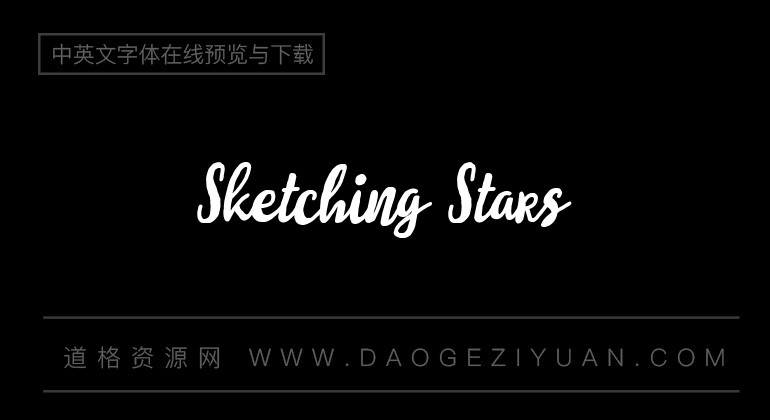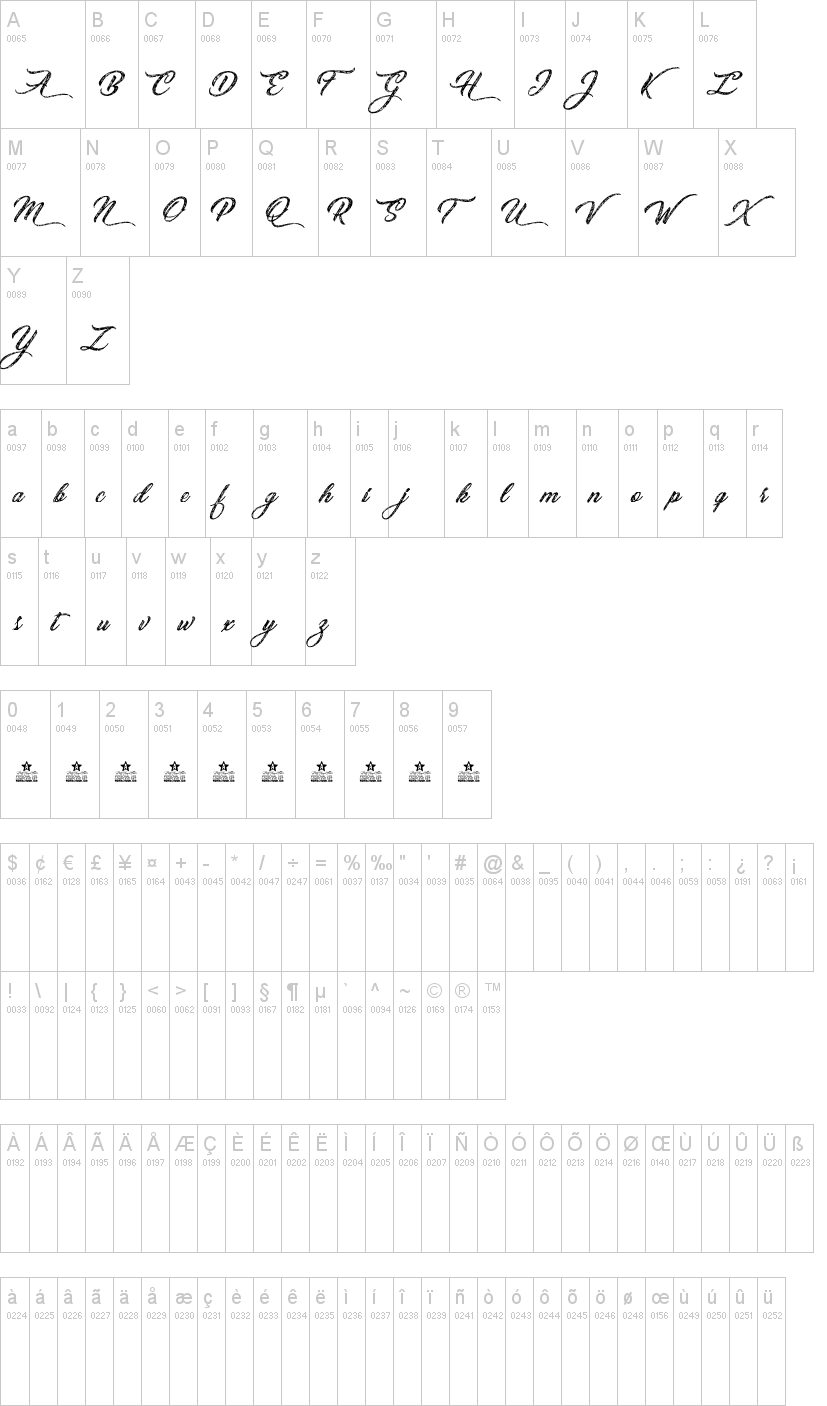
Sketching Stars
? Sketching Stars 字体是一款手绘风格的字体,它具有柔和的线条,可以更好地把握文本的精神内涵,更有助于传达出设计师的创意想法。它具有流畅的轮廓,可以更好地表达文本的主题,并且可以更好地展现出设计师的创意想法。它还可以支持多种语言,可以用于多种不同的设计项目。
Sketching Stars是一款非常不错的手写艺术字体,具有很好的视觉感,适合于文化类的宣传设计、商业类品牌的广告和产品包装设计以及个性化文字排版等较多场景。
Sketching Stars字符映射图